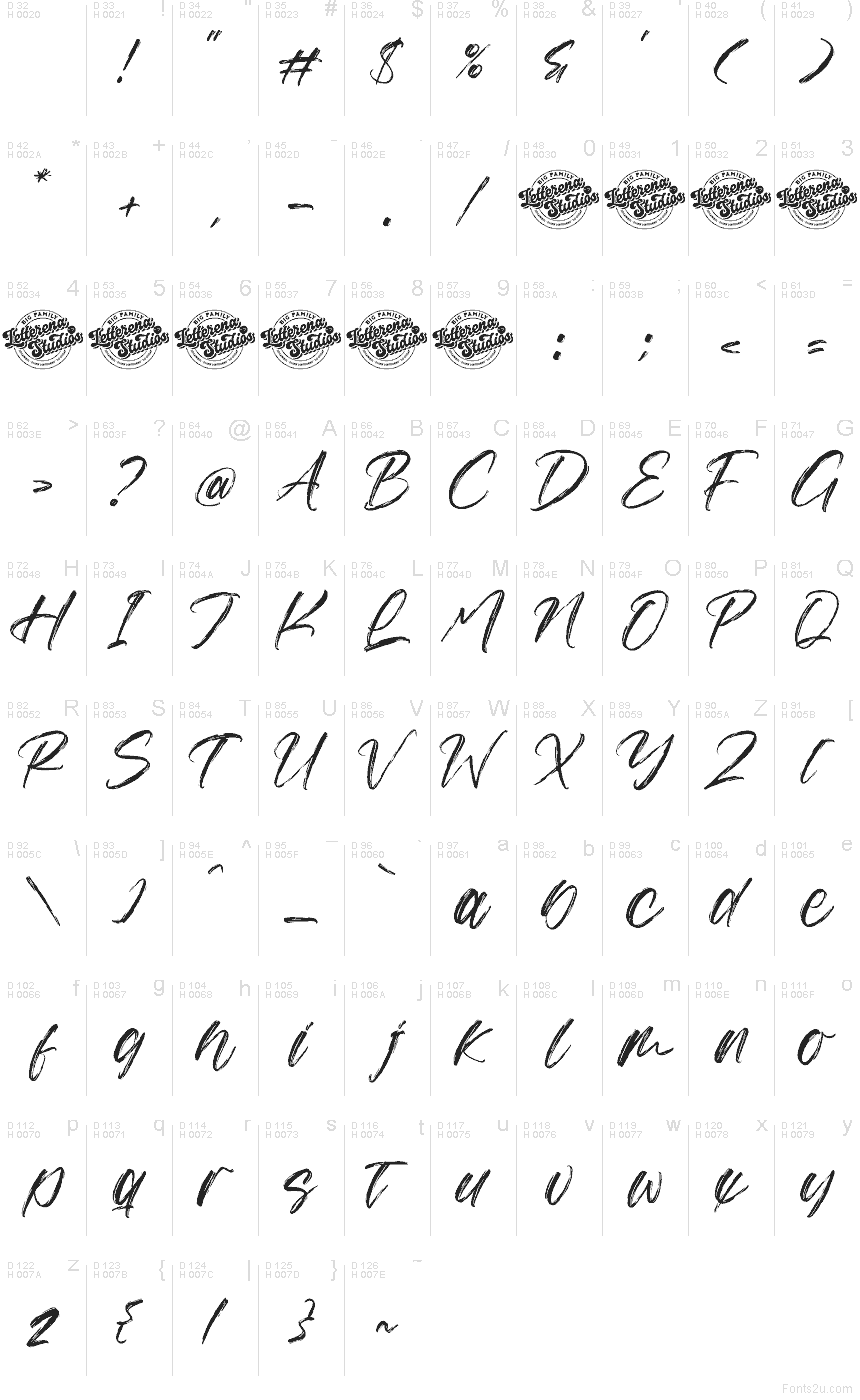
Anthony Dominate DEMO VERSION
Anthony Dominate от Letterena Studios — это бесплатный рукописный шрифт в стиле кисти, передающий быструю энергию модного эскиза. Его буквы отличаются длинными, хлесткими штрихами и воздушными петлями; благодаря сочетанию резких перепадов давления и свободных соединений, шрифт выглядит смело, плавно и немного драматично.
Он идеально подходит для брендинга, бутиковой упаковки, заголовков журналов, постов в соцсетях и титульных карточек, где шрифту важнее динамика, а не отточенность. Короткие цитаты, подписи и акцентные слова смотрятся в нем особенно выигрышно, так как эти размашистые штрихи и приподнятые выносные элементы придают даже короткой строке ощущение движения.